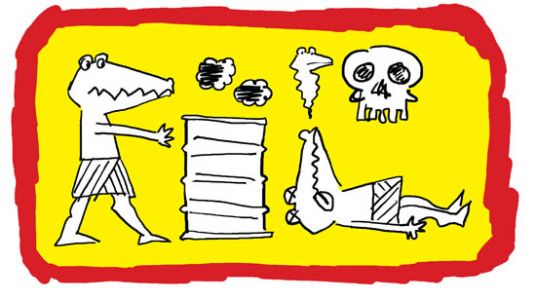
Warnzeichen für atomare Stoffe
dddddas gibts doch nicht! omg. :?
zuviele leute haben sich atomaren müll genähert
und sind daran gestorben? ähm, klar das muss an
dem zeichen liegen. logisch! auch das die kinder
(sind die nicht süß?) auf das mit dem totenkopf
zeigen. der sieht ja auch gefährlich aus. nur frage
ich mich wo sowas endet? dann müsste doch jedes
gefahrensymbol um einen totenkopf und ein picto-
grammmännlein erweitert werden. die spinnen doch alle.
ich klau jetzt die gelben schilder bei den kernkraftwerk
meines vertrauens und stell sie bei ebay rein –
als sammlerstück!
Ich glaube man muss sich damit abfinden, dass das funktionelle nicht immer das schönste ist :(
Das hier ist in diesem Zusammenhang auch interessant.
Hmm, nochmal drüber nachgedacht:
"Die Warnschilder und -aufkleber sollen überall dort angebracht werden, wo stark strahlende radioaktive Quellen stehen, die schwere bis lebensgefährliche Verletzungen verursachen können."
Disclaimer: Ich gehe davon aus, dass diese Schilder die bestehenden normalen Atom-Symbole *ergänzen*, nicht ersetzen. Sollte das tatsächlich nicht der Fall sein, und das alte Symbol durch das neue ausgetausch werden, ist meine folgende Argumentation für die Strahlenkatze (siehe Link oben --> Atomsemiotik).
Obenstehendes Zitat sagt mir, das Schild steht nur dort, wo es unmittelbar strahlt, wo man also schleunigst weg muss. Hier kann kaum das gleiche Symbol stehen, wie es als Warnhinweis z.B. auf Schränken für medizinisch-radioaktives Material angebracht ist.
Beim Schrank heißt das Symbol: "Da drin ist was gefährliches! Da wo du stehst passiert dir aber nichts".
Vor dem strahlenden lecken Atommüll-Fass muss stehen: "Scheiße, weg hier!" und nicht "Nicht öffnen, radioaktiv. Da wo du stehst passiert dir aber nichts".
Nun die Frage: Was wirkt da in dieser Situation besser, also schneller?
Ein (abstraktes) Symbol das wir zudem in anderem Kontext erlernt haben, oder eine Handlungsanleitung, die ebendieses Symbol beinhaltet, aber zusätzlich anweist sofort zu flüchten?
Dieses Schild ist auch keines, das man in 100m Entfernung sehen muss, sondern dann zur Handlung verleiten soll, wenn man sich direkt in Gefahr befindet, jede Vorwarnung also schon versagt hat.
Ich habe das Symbol (oder die Symbolabfolge) sofort verstanden, bevor ich den Text gelesen habe. Wenn nicht eindeutig, dann kann ich immerhin daraus lesen "Tod. Weg hier." Vor was ich dann flüchte (dem abstrakten Atomsymbol das strahlt) ist in dieser Situation primär egal.
Der Text hat mich dann hinterher verwirrt, bzw. nicht erklären können, wo und wie das Schild eingesetzt werden soll. Was ist nun schlecht, das Schild oder der Text?
das ist weder symbol noch zeichen, sondern eine tafel.
finde sie weder gelungen noch besser als das alte (sieht man ja auch, dass das alte symbol immernoch im neue vorkommt)
einfach ein anderer anwendungszweck, wobei ich denke das alte zeichen reicht völlig aus.
das neue "taferl" ist kein zeichen.
Der Fontblog meldet auch: "Das neue Zeichen ersetzt nicht das gelb-schwarze, sondern ergänzt es."
Somit bleibe ich bei der Argumentation: Die Ergänzung halte ich für sehr sinnvoll, da auf zwei verschiedene Situationen eingegangen wird, die mit einem gemeinsamen Symbol nicht befriedigend differenziert darzustellen sind.
Ob nun das neue Schild *gut* ist, oder ob es bessere Lösungen gäbe, ist eine andere Frage. Wie wäre es mit alternativen Vorschlägen zur Aussage "unfühlbare unmittelbare Gefahr, also weg hier mit dir, Leser"?
Edit: Es müsste natürlich ein Schild sein, das sofort funktioniert. Dass man der Gesellschaft ein neues Symbol einhämmert, wie das Atom-Zeichen, ist in diesem Falle kaum möglich. Fast 100% der Menschen wird dieses Schild wohl nie sehen.
Mich erinnert es ein wenig an die Wireless-access-Icon-Diskusion.
Das einzige, was mich wirklich irritiert, neben der unprofessionellen Umsetzung (siehe Fontblogkommentar Nummer 7), ist die Tatsache, dass es Schwarz auf Rot ist, was meiner Meinung nach schlechter zu lesen ist als Schwarz auf Gelb :? Im ungünstigsten Fall geht man eben erst mal zur Gefahrenquelle hin, schaut und flüchtet dann.
Ich finde das Atomarestrahlungzeichen erinnert einfach
zu sehr an Windkraft ;-)
Hätte besser komplett verändert werden sollen?
Also bei dem Zeichen müsste man schon sehr blöd sein, um nachzusehen, bevor man flüchtet. Wobei wir ja wissen: Dummheit ist keine Seltenheit!
Dass das neue Zeichen von der Symbolik besser funktioniert als das bisherige scheint mir außer Zweifel. Das alte Symbol setzte doch Bildung voraus — ich bin mir sicher, dass wir in DACH zahlreiche Leute finden, die die Bedeutung dieses Symbols nicht kennen. Der Totenschädel dürfte hingegen sogar im Dschungel von Brasilien Alarm im Kopf des Betrachters auslösen.
Rot halte ich auch für die bessere Farbe, weil ich glaube, dass sie Gefahr noch mehr verdeutlich als Gelb. Nur die Entscheidung für schwarze Symbole auf dem roten Grund halte ich für bedenklich, gerade bei schlechten Sichtverhältnissen — da helfen die weissen Outlines wohl auch nicht mehr viel. Ob der Totenschädel jedoch in einer Ausführung in Weiss beim Ureinwohner im Dschungel noch so klar verständlich war wie in dieser recht plastischen Umsetzung … ?
zu den symbolen von aicher (und du weißt ich bin ein aicher fan)
gab es schon in den olympiaden vorher solche zeichen. "biathlon" erkennt man nur wenn man weiß was "biathlon" ist.
verkehrsschilder müssen auch erlernt werden.
das neue buch von kneidl, krampen und götte wird wohl eher klarheit bringen. da wurde ja grundlagenforschung betrieben. auf das ergebnis bin ich dann gespannt.